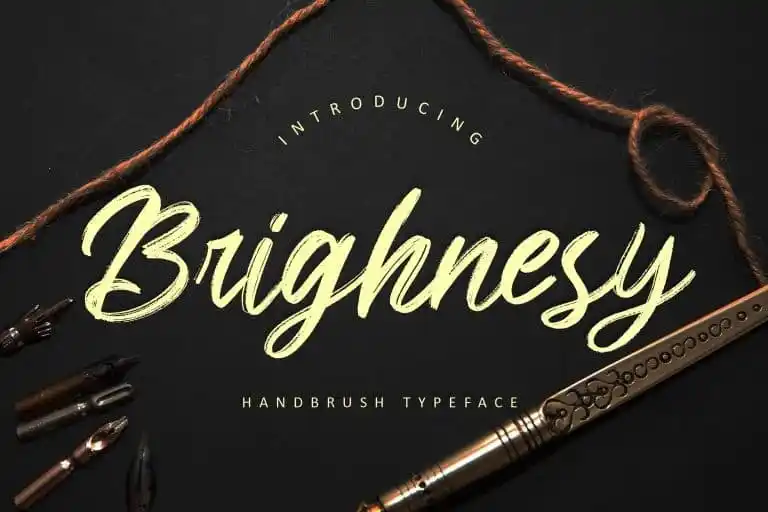
Brighnesy Brush Font – Fonte Grátis
Brighnesy Brush Font
A Brighnesy Brush Font é uma fonte criada com a ajuda de um penhoar. Ela possui traços elegantes e fluidos, perfeita para projetos que precisam de um toque handwritten, como logotipos, embalagens de produtos, anúncios ou até mesmo inviáveis e cartões de visita. Foi desenvolvida pela Creatype Studio no site 99designs. Seja qual for o seu projeto, seja ele uma marca criativa, um enfeite para sua página social ou até mesmo um design para embalagens de produtos, a Brighnesy Brush Font traz para você aquela elegância e sofisticação que fazem parte do estilo handmade. Seja em estilos tipográficos mais tradicionais, ou em aplicações mais criativas, como design gráfico para editoriais de fotografia ou até mesmo uma capa de livro – o Brighnesy Brush Font trará aquele toque especial e único que faz a diferença. Este é um verdadeiro trunfo para designers e criadores de conteúdo buscando tornar seus projetos ainda mais singulares. Tudo isso, em um design elegante e fluido, que permite que você tenha o melhor de ambas as coisas: texto visualmente belo e uma mão cheia de estilo.